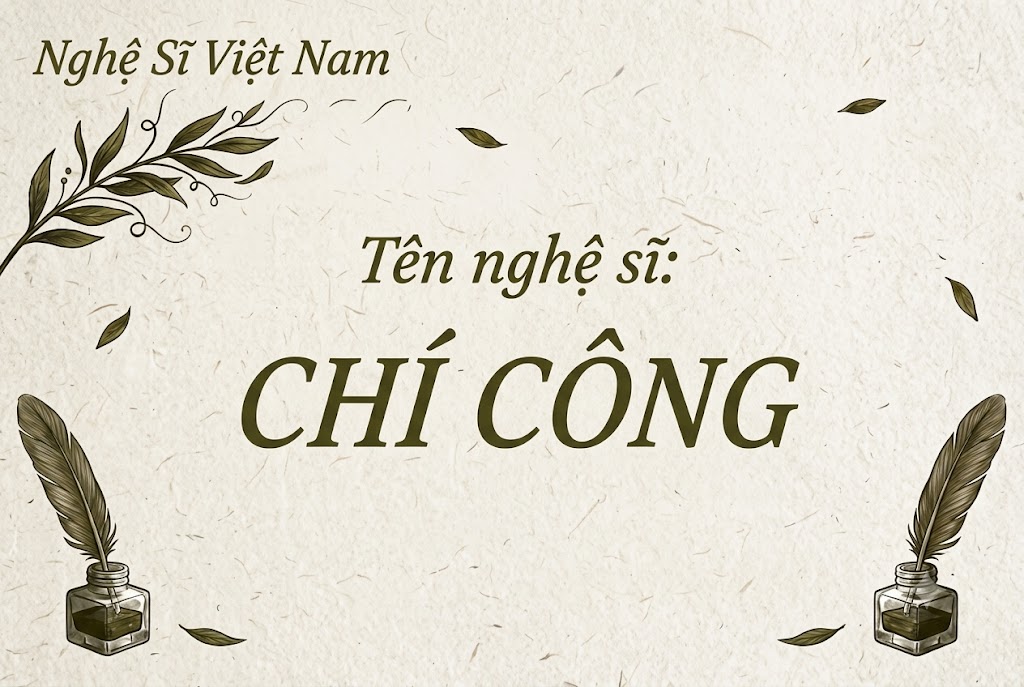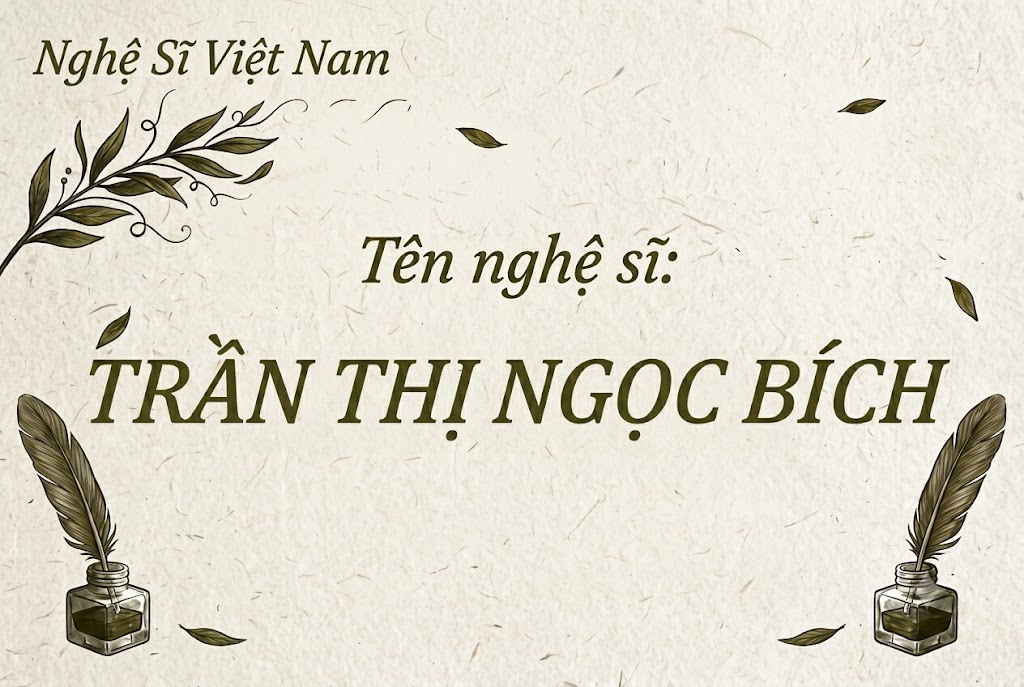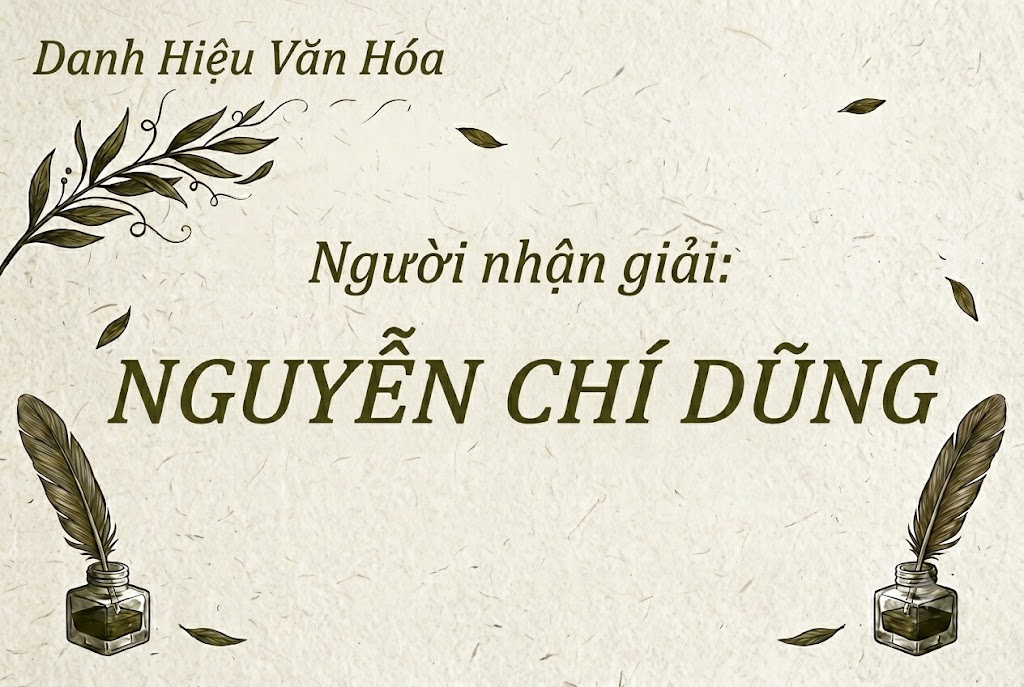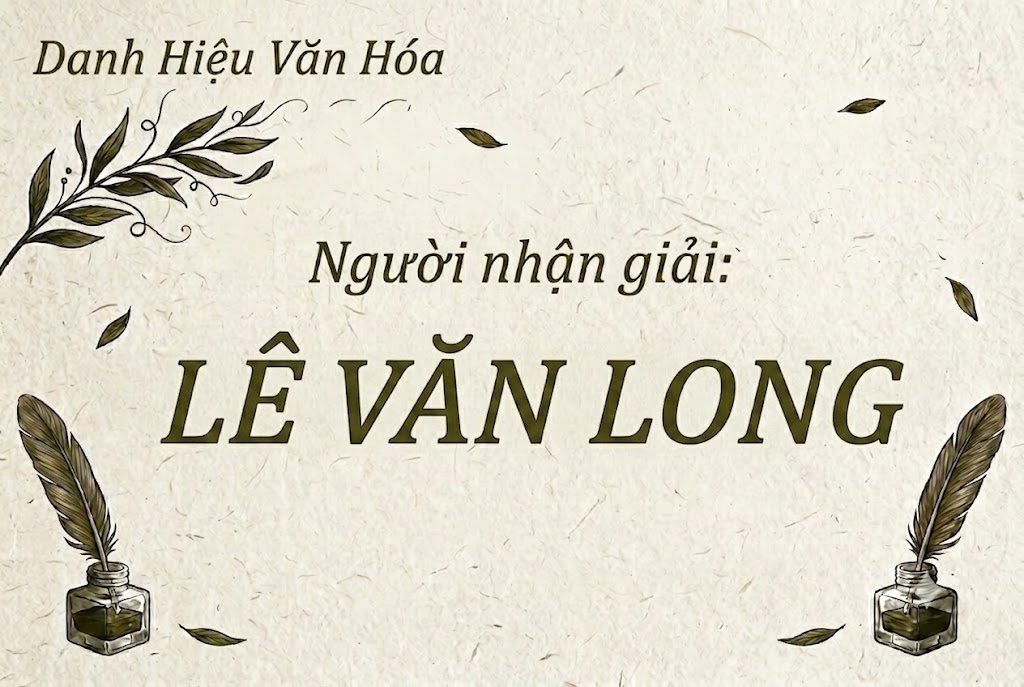
1FTV HF Gesco Ita
Trong việc tối ưu hóa giao diện nội dung số, các phông chữ không chân dáng nghiêng nhẹ luôn được ưu tiên để tạo cảm giác chuyển động linh hoạt.
Một font chữ gọn gàng, tinh tế nhưng vẫn giữ được sự trẻ trung sẽ giúp các dòng tiêu đề hoặc phụ đề của bạn trở nên cuốn hút hơn.
Nếu bạn đang tìm kiếm một thiết kế hiện đại phục vụ việc biên tập video ngắn hay làm hình ảnh quảng cáo, thì font 1FTV HF Gesco Ita chính là lựa chọn lý tưởng.
Giới thiệu về font 1FTV HF Gesco Ita
Font 1FTV HF Gesco Ita là một bộ chữ thuộc thể loại display không chân mang phong cách hiện đại, thanh thoát và đầy tính ứng dụng.
Nhờ thông số kĩ thuật tối ưu này, phông chữ có khả năng hiển thị sắc nét tuyệt đối trên các phần mềm thiết kế đồ họa mà không lo lỗi răng cưa.
Đặc điểm nổi bật của phong cách thiết kế HF Gesco Ita
Sức hút lớn nhất của font 1FTV HF Gesco Ita đến từ độ nghiêng nhẹ đầy tinh tế kết hợp cùng các nét chữ không chân hiện đại.
Độ nghiêng này không quá thô cứng như các dòng font thể thao thuần túy, mà mang lại một cảm giác uyển chuyển, thanh lịch và rất dễ chịu cho mắt.
Bộ font hỗ trợ đầy đủ cả hệ thống chữ cái thường bên cạnh hệ thống chữ viết hoa, giúp người dùng dễ phân tách các tầng nội dung văn bản.
Khoảng trống bên trong và khoảng cách giữa các từ được tính toán khoa học, giúp tiêu đề luôn rõ ràng ngay cả khi đặt trên các phần nền phức tạp.
Để phông chữ vận hành mượt mà trên mọi hệ thống máy tính, phiên bản font 1FTV HF Gesco Ita đã trải qua quy trình xử lý thông số kĩ thuật kỹ lưỡng.
Hệ thống khoảng cách chữ và độ giãn dòng đã được căn chỉnh chuẩn xác, giúp văn bản luôn liền mạch và giữ được sự thoáng đãng.
Bên cạnh hệ thống chữ cái hoa và thường đồng bộ, phông chữ còn tích hợp đầy đủ dãy số từ 0-9 cùng hệ thống các ký tự đặc biệt, dấu câu thông dụng (.,;: ' " (!?) +-*/=).
Đặc biệt, bản tối ưu này giúp bạn hoàn toàn yên tâm sáng tạo các nội dung tiếng Việt mà không gặp phải tình trạng lỗi hiển thị khi gõ.
Hình ảnh demo thực tế của font 1FTV HF Gesco Ita
Để giúp bạn dễ dàng hình dung khả năng co giãn và hiển thị linh hoạt của phông chữ này trên các kích thước khác nhau, hãy cùng xem qua bảng mô phỏng thực tế:
Kích thước nhỏ (12pt – 24pt): Các nét chữ mảnh và độ nghiêng vừa phải vẫn hiển thị rất rõ ràng, ngay ngắn, dễ đọc trên màn hình điện thoại di động.
Kích thước lớn (36pt – 72pt): Đây là không gian lý tưởng để font chữ phô diễn toàn bộ sự thanh lịch, tạo hiệu ứng thị giác hiện đại cho các tiêu đề chính.
Ứng dụng của font HF Gesco Ita trong thiết kế đồ họa và làm video
Sở hữu nét cá tính thanh lịch và cấu trúc hoa – thường linh hoạt, font 1FTV HF Gesco Ita mở ra không gian ứng dụng rộng lớn cho các dự án truyền thông:
Thiết kế ảnh thu nhỏ mạng xã hội: Đây là lựa chọn tuyệt vời cho các chủ đề về phong cách sống, vlog cá nhân, review công nghệ hoặc xu hướng giới trẻ để thu hút người xem bấm vào.
Làm tiêu đề và phụ đề cho video ngắn: Kiểu chữ nghiêng thanh thoát này rất thích hợp để làm phụ đề (subtitle) chạy chữ hoặc tiêu đề mở đầu cho video Tiktok, Reels, giúp giữ chân người xem.
Banner và poster quảng cáo doanh nghiệp: Hoàn hảo cho các poster giới thiệu sản phẩm, banner chương trình ưu đãi hoặc các ấn phẩm truyền thông đòi hỏi tính chuyên nghiệp, gọn gàng.
Nhận diện thương hiệu phong cách tối giản: Phù hợp làm logo dạng chữ, biểu ngữ hoặc thiết kế nhãn mác cho các thương hiệu thời trang, studio sáng tạo hoặc các công ty dịch vụ hiện đại.